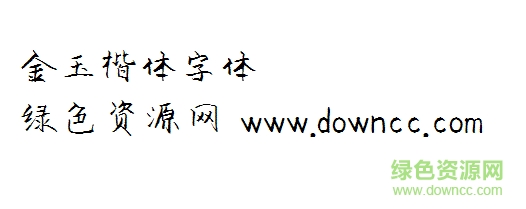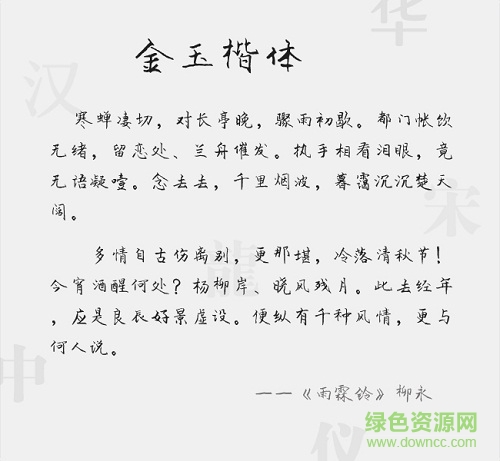
金玉楷體字體是一款時(shí)尚酷炫風(fēng)格字體軟件,金玉楷體筆畫隨意灑脫,卻別有一番韻味,介于楷書與行書之間,創(chuàng)意獨(dú)特,深受廣大書法家喜愛,還有更多好看字體歡迎來綠色資源網(wǎng)下載體驗(yàn)!
金玉楷體字體造型規(guī)整,富于力度,給人以簡(jiǎn)潔爽朗的現(xiàn)代感,有較強(qiáng)的視覺沖擊力,這種個(gè)性的字體,適合于機(jī)械科技等主題。